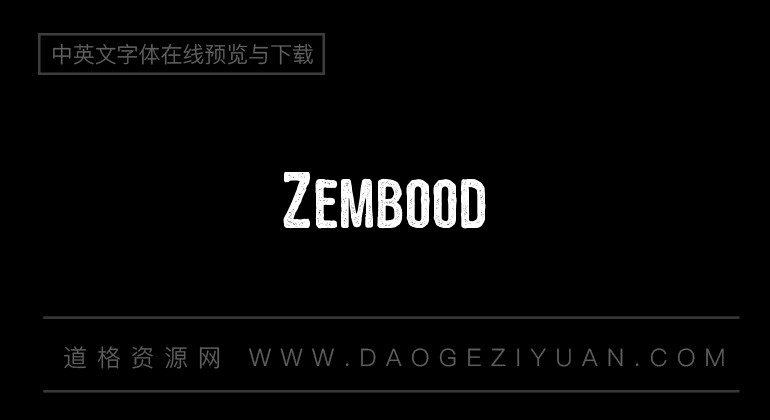
Zembood 字体是一款具有现代感的拉丁字体,由设计师Adam Ladd创作。它拥有清晰的线条和活力四射的笔画,而且具有极佳的可读性,可以用于各种文档和平面设计中。它的字体特性比较复杂,有粗体,斜体,带有衬线的字体,以及其他的多种字体变体,可以满足不同的需求。内容介绍
Zembood是一款非常不错的手写艺术字体,具有很好的视觉感,适合于文化类的宣传设计、商业类品牌的广告和产品包装设计以及个性化文字排版等较多场景。